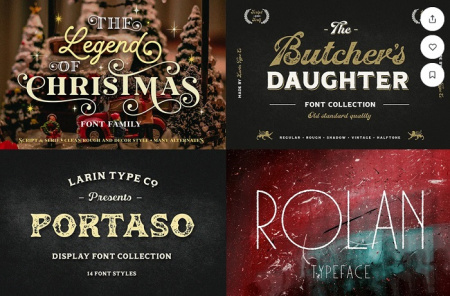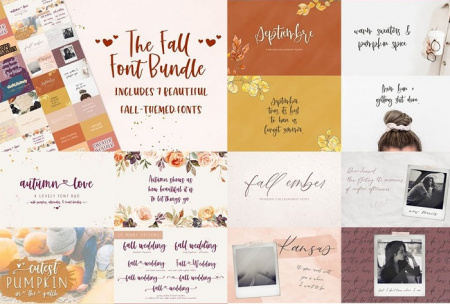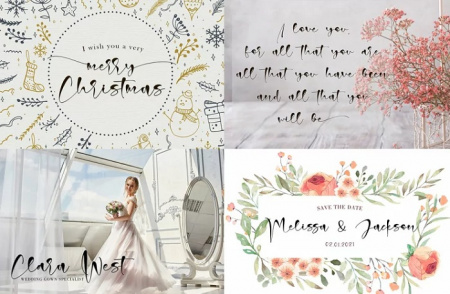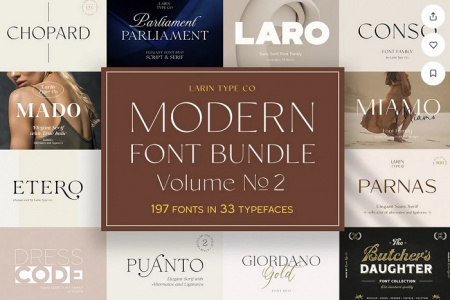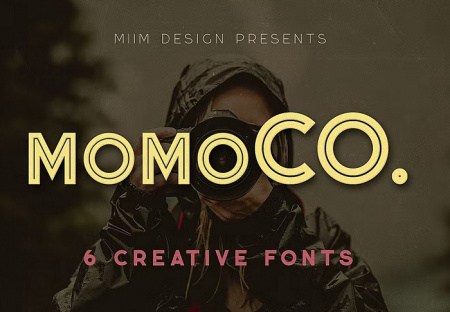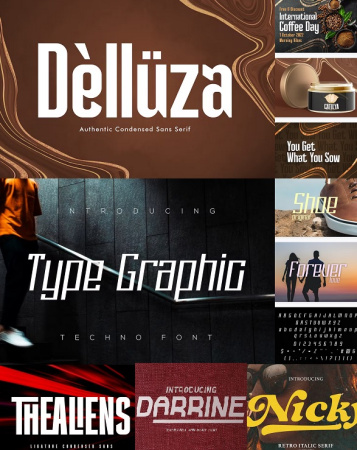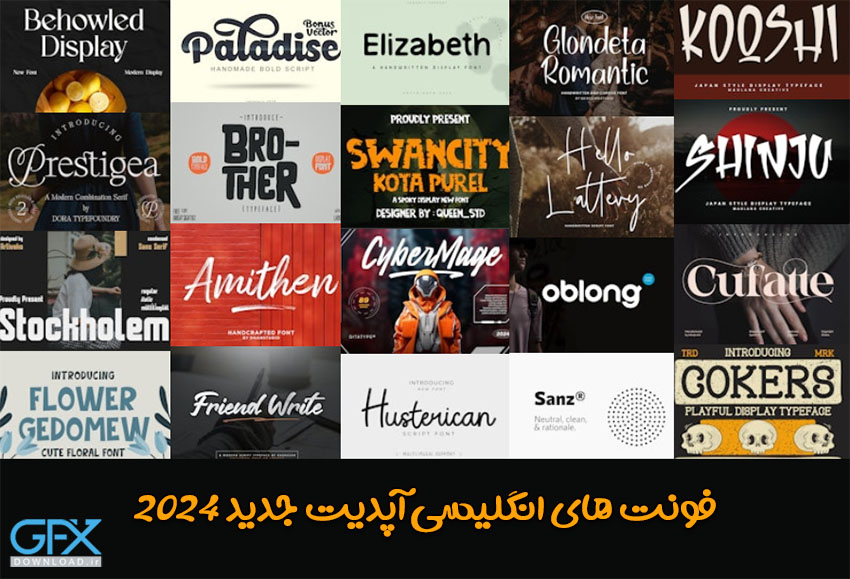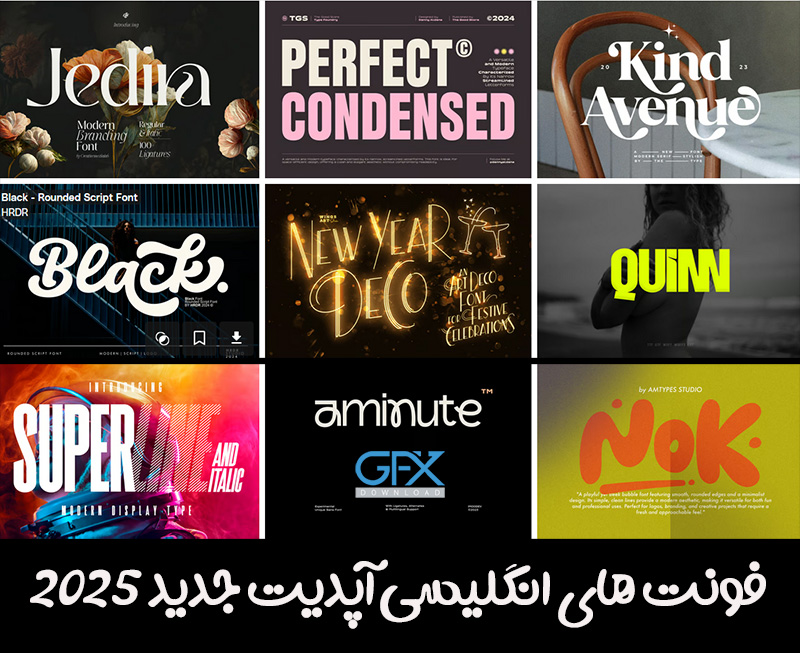
پکیج کامل 500 فونت انگلیسی برای اینشات ، فتوشاپ و طراحان
پک فونت انگلیسی جی اف ایکس دانلود
پک فونت انگلیسی وبسایت جی اف ایکس دانلود یکی از بهترین و کاملترین پکیج های فونت های انگلیسی با ارزش بیش از 1000 دلار می باشد.در این پکیج بیش از 500 فونت مختلف با موضوعات زمستان ، کریسمس ، فونت های انگلیسی مدرن ، اسکریپت ، دست نویس ، فروش ویژه ، براش و ...قرار گرفته است.شما می توانید از این پکیج برای طراحی های مختلف استفاده نمایید.همچنین می توانید در تمامی نرم افزار های گرافیکی مانند فتوشاپ ، کورل ، ایلستریتور و برنامه های موبایل مانند اینشات از این مجموعه استفاده نمایید.در ادامه می توانید پیش نمایش پکیج را مشاهده و فایل اصلی را با تهیه اشتراک یا خرید فایل از جی اف ایکس دانلود دریافت کنید.
پکیج 500 فونت انگلیسی برای فتوشاپ ، اینشات و طراحان گرافیکی
فونت های انگلیسی مدرن ، اسکریپت ، دست نویس
✅ فونت های مناسبتی فروش ویژه ، زمستان ، کریسمس و ...
20 فونت انگلیسی جدید آپدیت 2024 به مجموعه اضافه شد.
فونت های انگلیسی جدید آپدیت 2025 به مجموعه اضافه شد.
پک کامل 500 فونت انگلیسی برای اینشات ، فتوشاپ و طراحان
پک فونت انگلیسی کریسمس
پکیج فونت انگلیسی مدرن فتوشاپ
فونت انگلیسی momoco برای طراحی در فتوشاپ
پک فونت انگلیسی دست نویس
پکیج کامل فونت انگلیسی جی اف ایکس دانلود آپدیت شماره 1
در این آپدیت 5 مجموعه فونت انگلیسی زیبا و جذاب با نام های Darrine ، Type graphic Font ، Nicky ، Thealiens و Delluza قرار داده شده است که می توانید آن ها را دریافت نمایید.شما می توانید از این فونت های انگلیسی برای طراحی های مختلف در موبایل و نرم افزارهای دسکتاپ استفاده نمایید.ما در این جا سعی داریم با کیفیت ترین پکیج یا مجموعه فونت های انگلیسی را با قیمت مناسب در اختیار شما قرار دهیم.